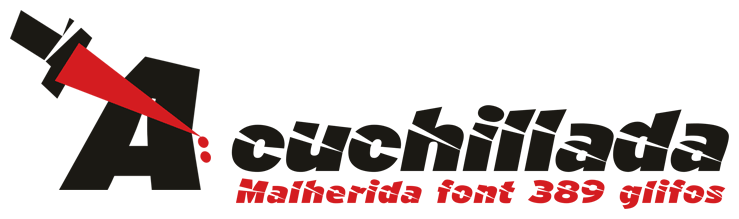
A Cuchillada
A Cuchillada à  by deFharo
-La tipografía A cuchillada es un experimento expresionista del dolor del autor por la muerte prematura de un gran amigo.
-Typography A knife is a pain expressionist experiment typographer by the untimely death of a great friend.